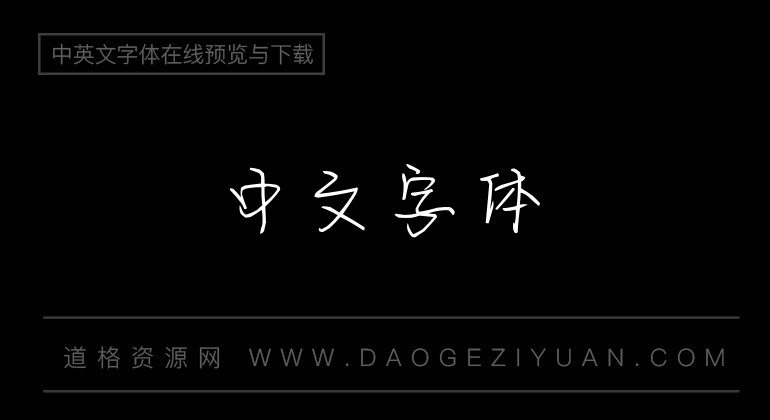
伯乐俏皮体
伯乐俏皮体是一款活泼可爱的中文字体,它是由英文字体“Comic Sans”改编而来,拥有着浓厚的童趣风格,采用更加精致的视觉语言,更有趣的符号,更加灵动的曲线,以及更多的表情符号,让字体更加有趣可爱。伯乐俏皮体适用于各种活动、展览、广告、商业等场合,可以让您的设计更有个性,更有趣,同时也可以让您的设计更加活泼可爱。
伯乐俏皮体是一款非常不错的手写艺术字体,具有很好的视觉感,适合于文化类的宣传设计、商业类品牌的广告和产品包装设计以及个性化文字排版等较多场景。